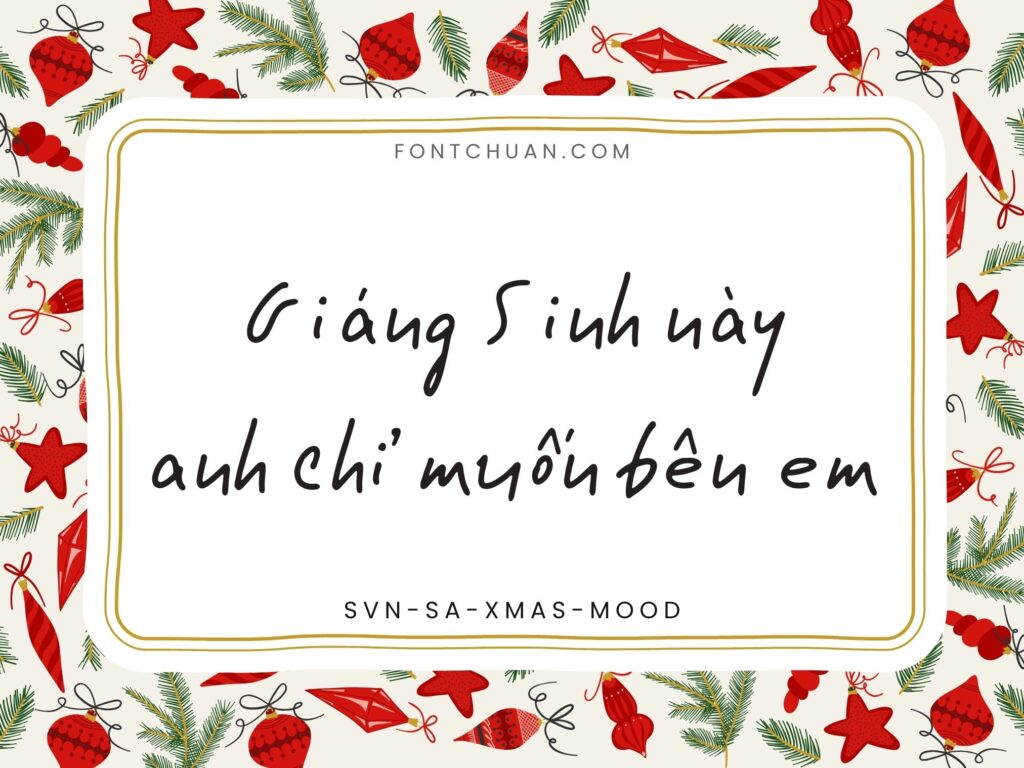
Font SVN Sa Xmas Mood Việt Hóa
Font SVN-SA Xmas Mood là phiên bản Việt hóa của kiểu chữ SA Xmas Mood, được thực hiện bởi STYLEno.1 Fonts. Đây là một font chữ viết tay mang phong cách vui nhộn và thân thiện, được thiết kế đặc biệt cho các dịp Giáng sinh. Font này lý tưởng cho việc tạo chữ ký Giáng sinh, thiệp chúc mừng, sticker, trích dẫn và trang trí ảnh trên mạng xã hội. Với các nét chữ mềm mại và đáng yêu, SA Xmas Mood mang đến không khí lễ hội ấm áp và vui vẻ cho các thiết kế của bạn.
SVN-SA Xmas Mood phù hợp cho các dự án thiết kế liên quan đến Giáng sinh, như thiệp mời, poster, bao bì sản phẩm và các ấn phẩm truyền thông. Các ngành nghề như quảng cáo, giáo dục và ẩm thực có thể tận dụng font này để tạo điểm nhấn trong thiết kế. Ngoài ra, font cũng thích hợp cho các sự kiện như Tết, Sinh nhật và các lễ hội khác.